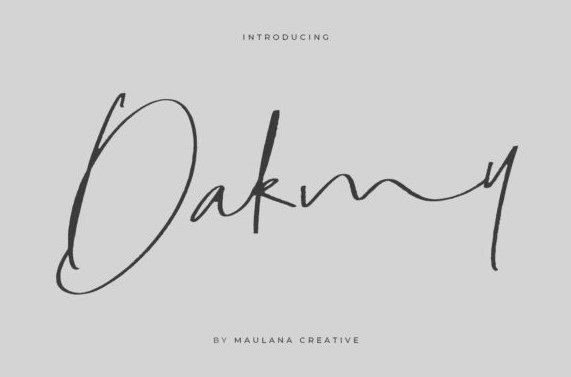
Название: Dakmy Font
Dakmy - это тонкий и элегантный рукописный шрифт.
Его четкие и хорошо закругленные буквы делают этот шрифт шедевром.
Влюбитесь в его невероятно универсальный стиль и используйте его для создания эффектных дизайнов!
Название: Dakmy Font
Dakmy - это тонкий и элегантный рукописный шрифт.
Его четкие и хорошо закругленные буквы делают этот шрифт шедевром.
Влюбитесь в его невероятно универсальный стиль и используйте его для создания эффектных дизайнов!